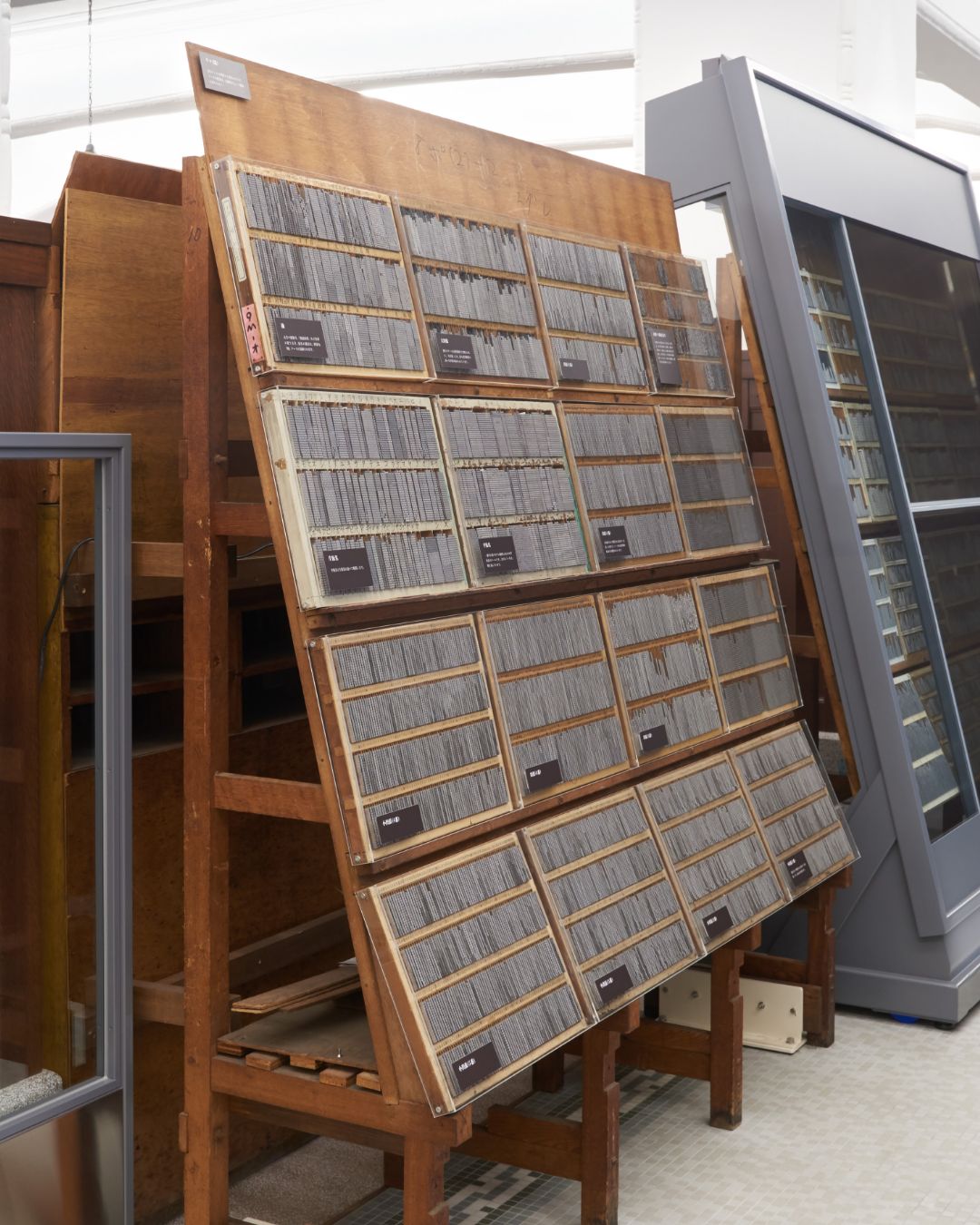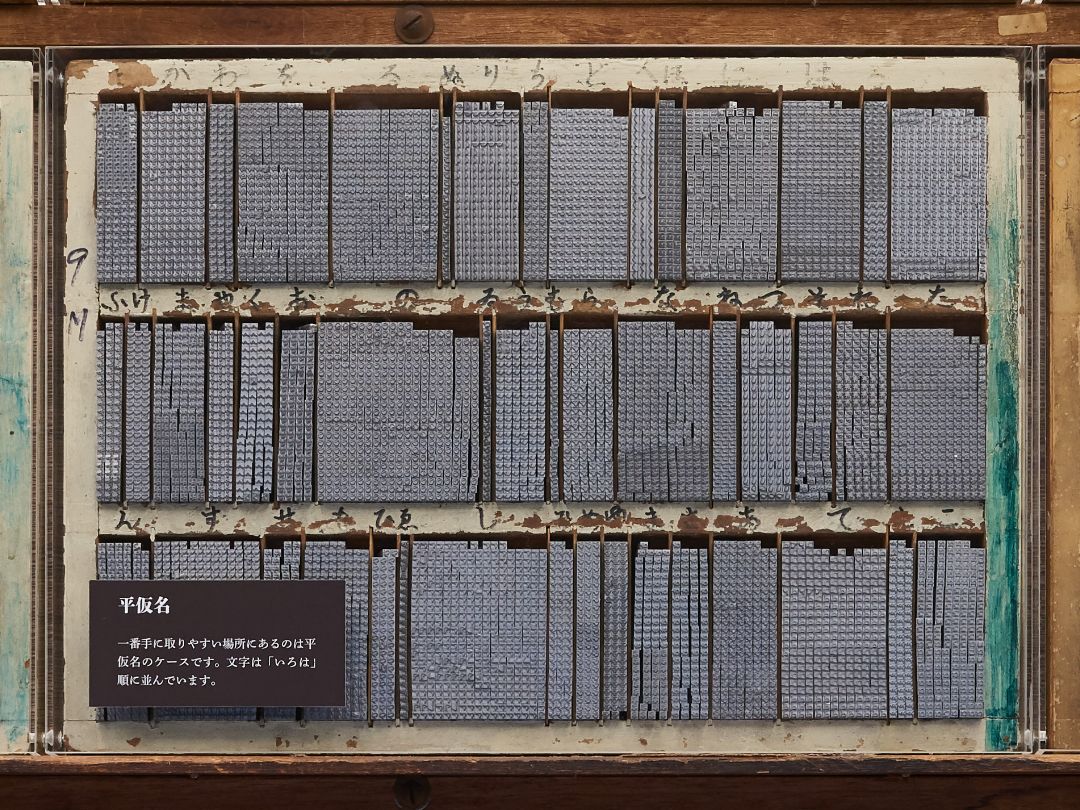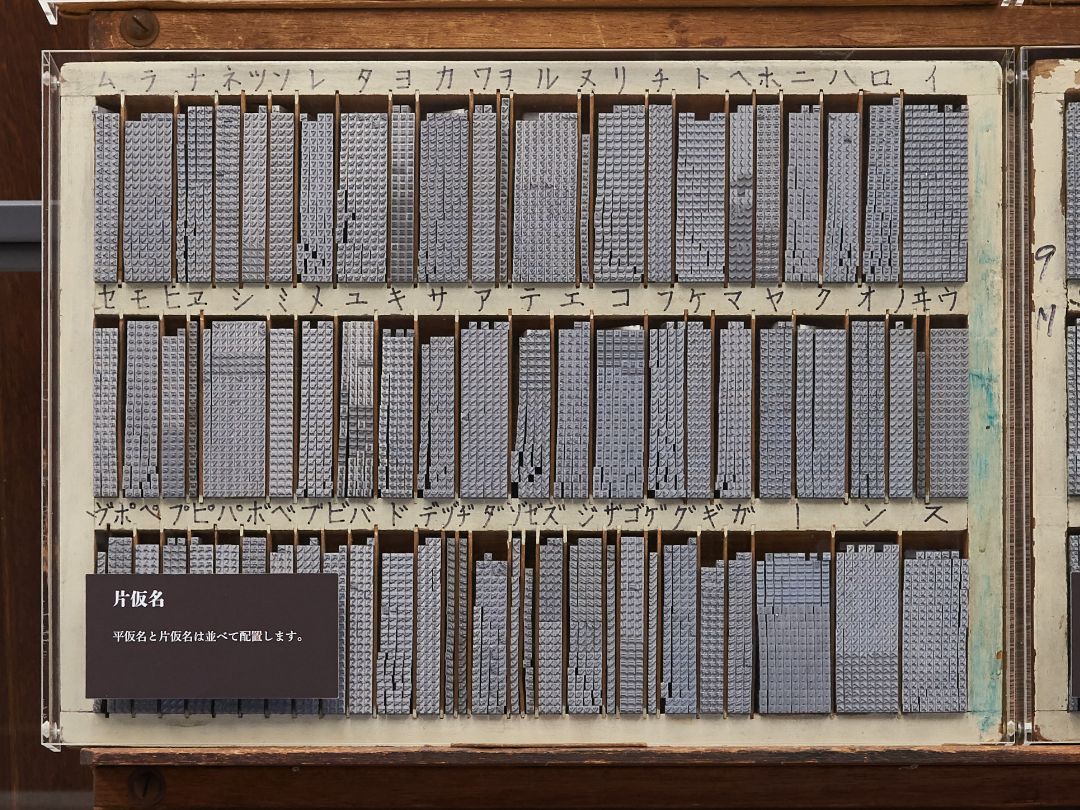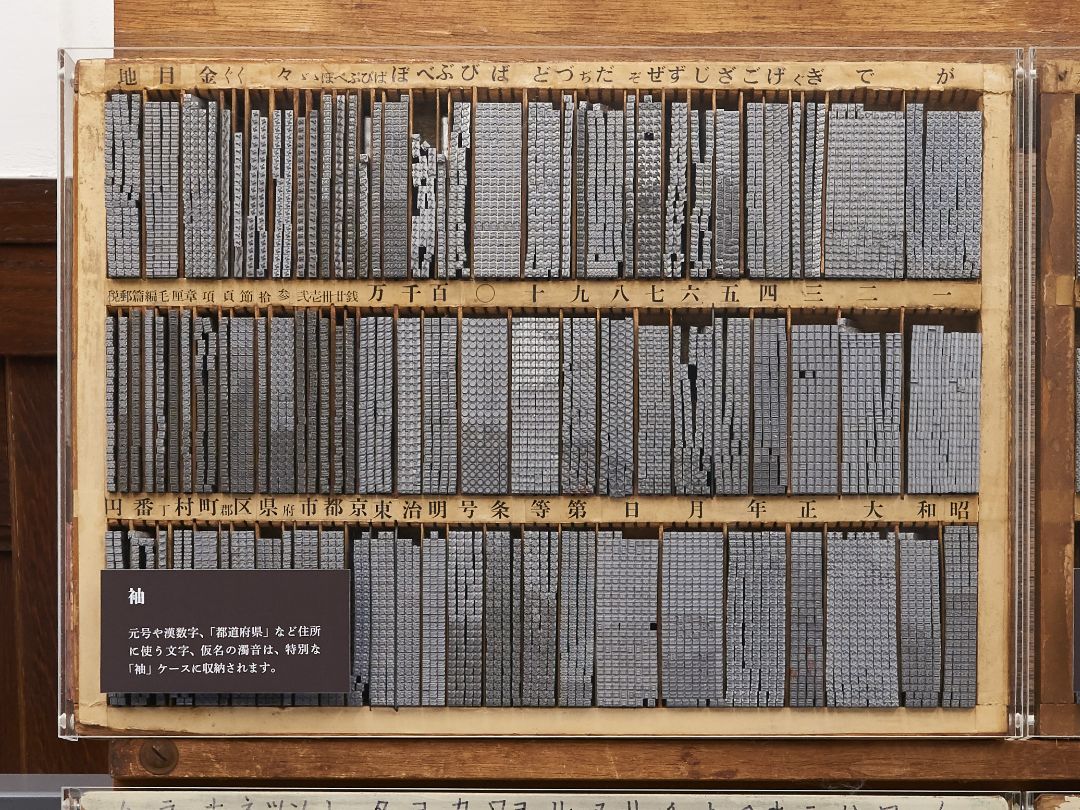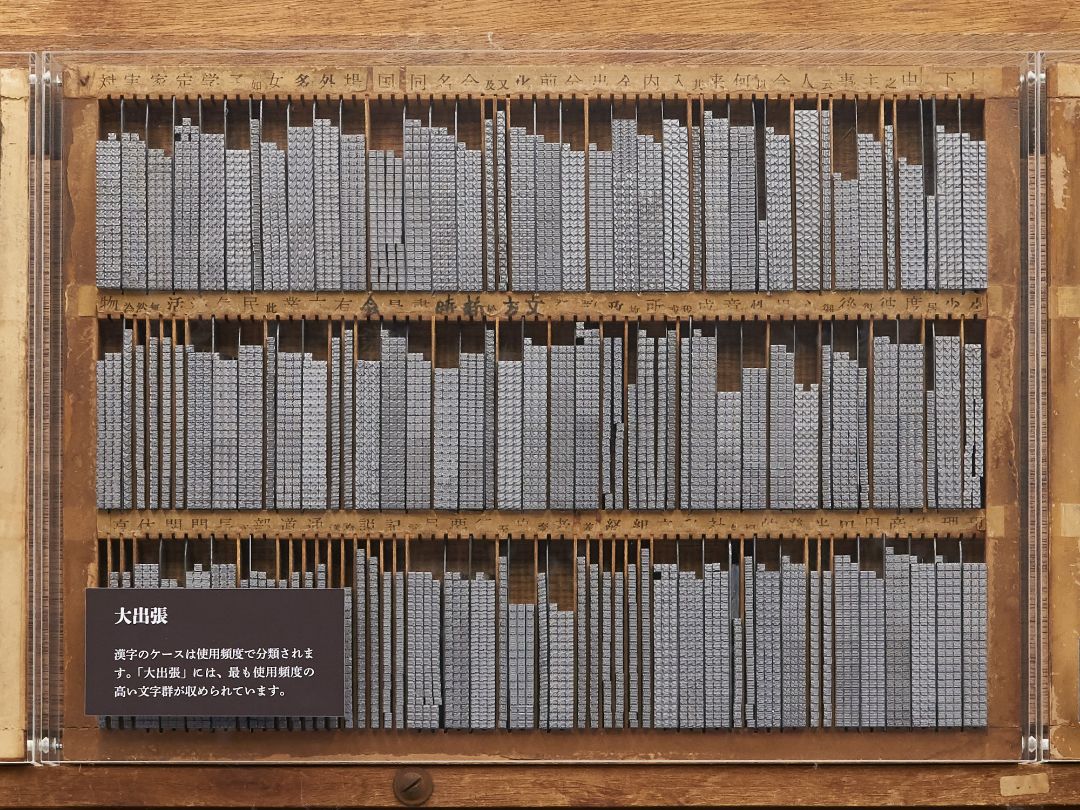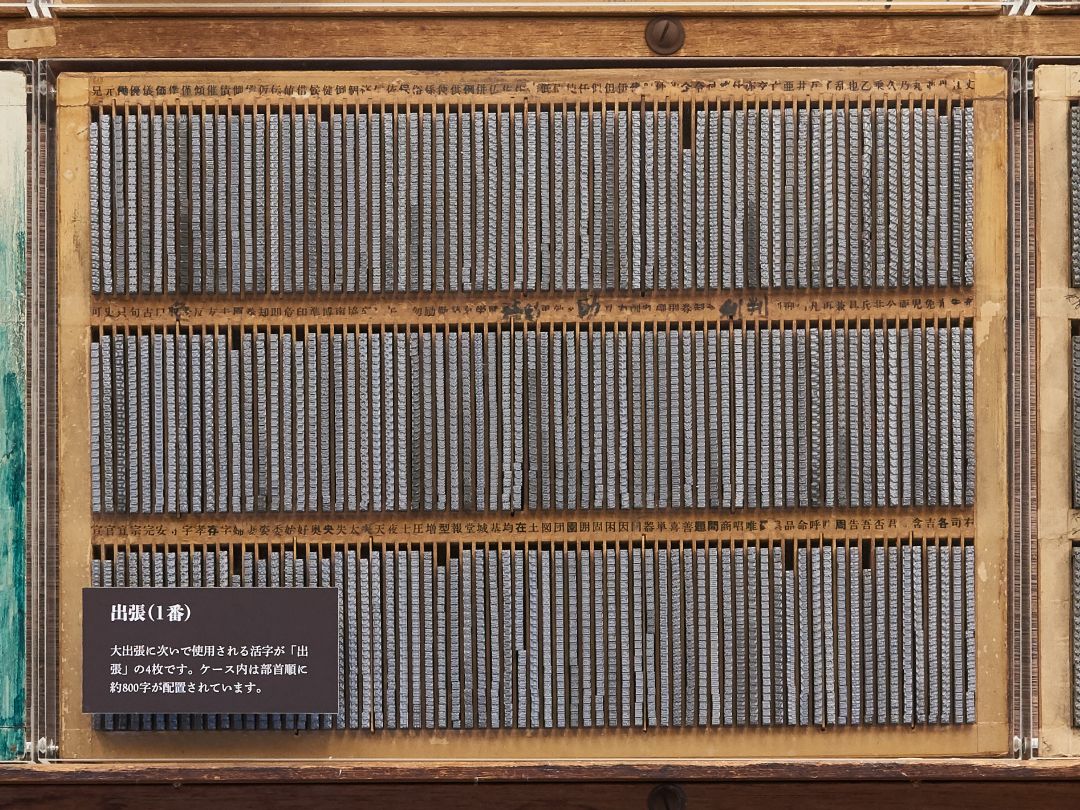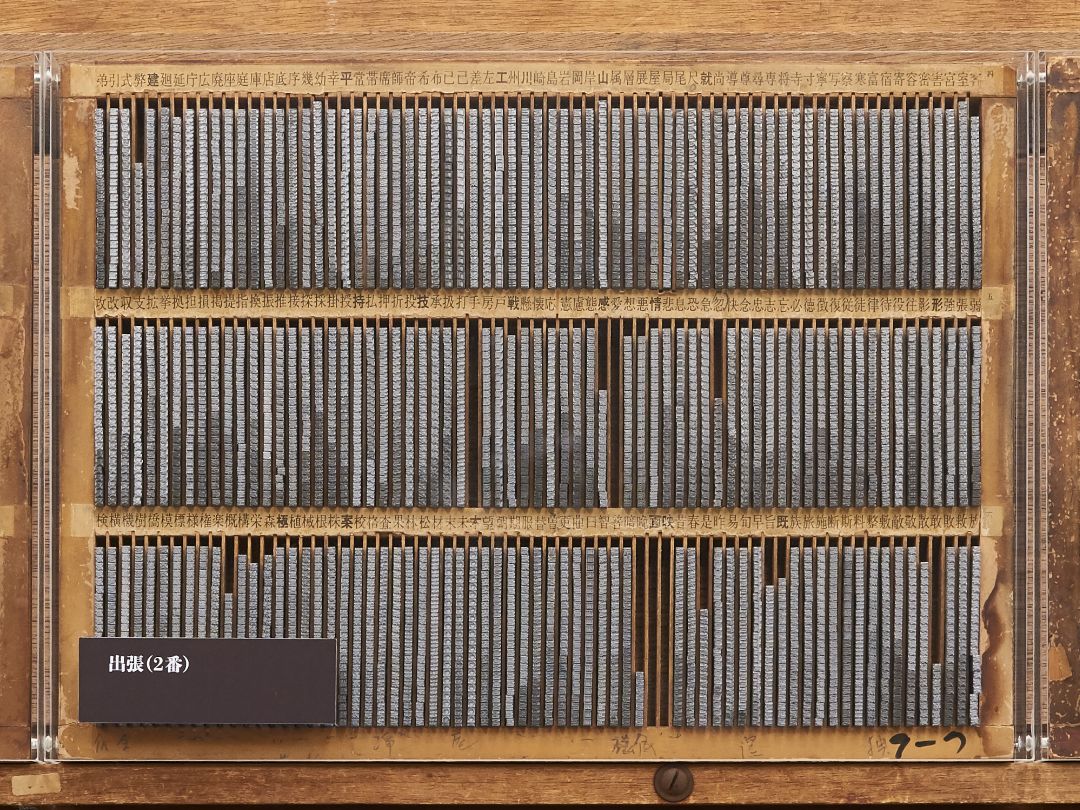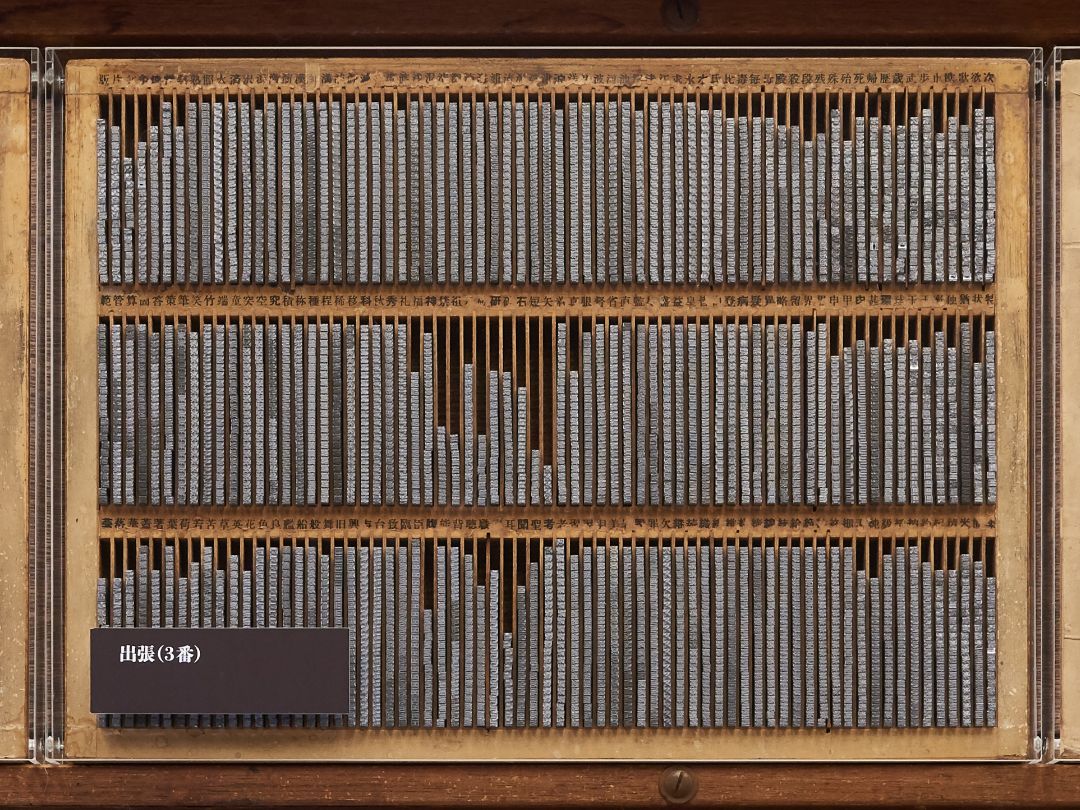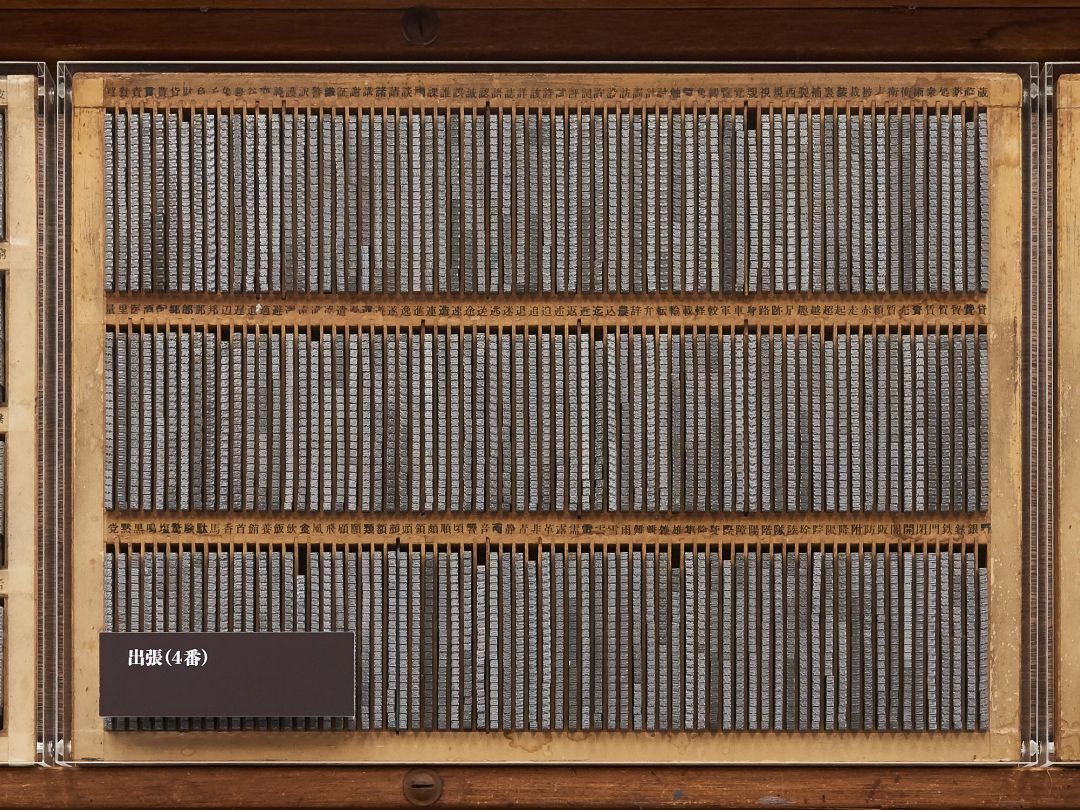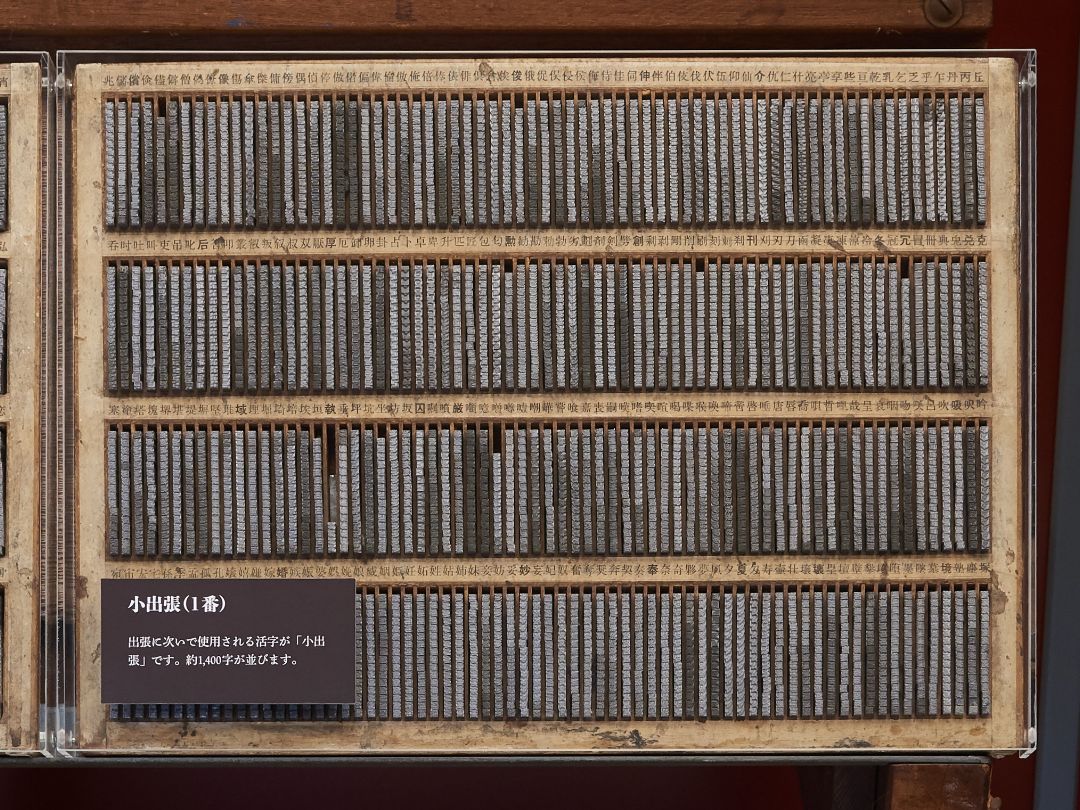
三、文選
1文字ずつ活字を拾って文章をつくります。
原稿に合わせて活字を拾う工程が「文選」です。鋳造した活字は、使用頻度ごとに区分され、文字種・部首順に棚に配列されます。職人1人の使う範囲は、平仮名・片仮名と、使用頻度の高い漢字約2,500字です。
文選は、膨大な文字数を使用する漢字圏だからこそ見ることのできる貴重な工程です。
ウマ(馬)
活字ケースを配置する専用の台です。ケースの配置は、印刷所によって微妙に異なります。
平仮名
一番手に取りやすい場所にあるのは平仮名のケースです。文字は「いろは」順に並んでいます。
片仮名
平仮名と片仮名は並んで配置されます。
袖
元号や漢数字、「都道府県」など住所に使う文字、仮名の濁音は、特別な「袖」ケースに収納されます。
大出張 おおしゅっちょう
漢字のケースは使用頻度で分類されます。「大出張」には、最も使用頻度の高い文字群が収められています。
出張
大出張おおしゅっちょうに次いで使用される活字が「出張」の4枚です。ケース内は部首順に約800字が配置されています。
出張(1番)
出張(2番)
出張(3番)
出張(4番)
小出張 こしゅっちょう
出張に次いで使用される活字が「小出張」です。約1,400字が並びます。
小出張(1番)
小出張(2番)
小出張(3番)
小出張(4番)
小出張(5番)
直彫り(新刻)活字
原稿の中に母型のない文字があった時は、手で活字を彫る「直彫り」職人の出番です。指先よりも細い鉛合金の先端に、文字を原寸・左右反転の状態で彫っていきます。印刀で直接彫った活字は文字面が輝いています。
直筆原稿(複製)
1906(明治39)年、雑誌『ホトトギス』に夏目漱石が発表した『坊っちゃん』の直筆原稿の一部(複製)です。